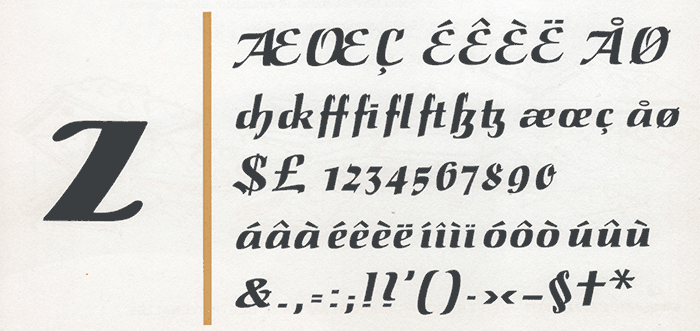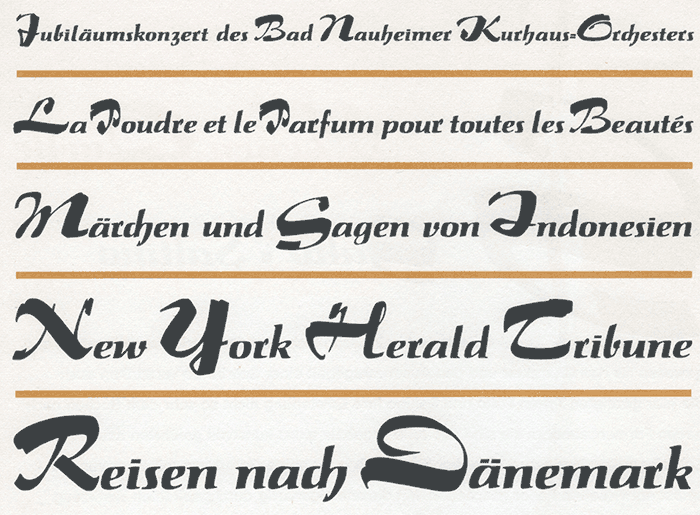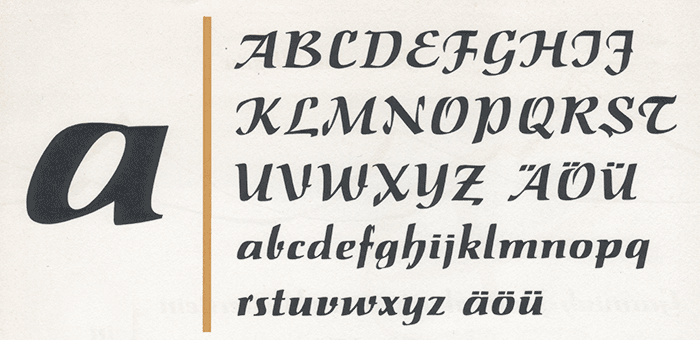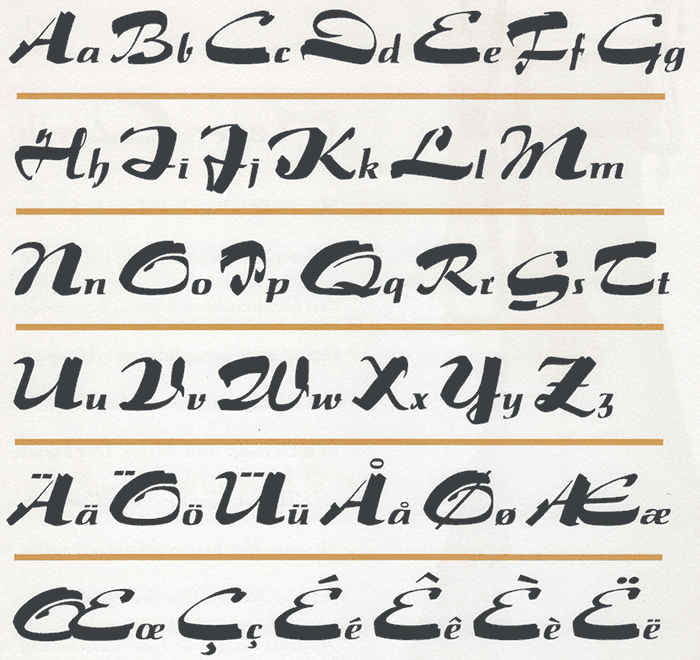
- 1952
- Antiqua Schreibschrift
Die zusammengehörigen Schriften Salto und Saltino erschienen ab 1952 bei der Schriftgießerei Gebr. Klingspor. Die Kleinbuchstaben wurden mit einer von Hoefer eigens entwickelten Breitfeder entwickelt. Je nachdem, welche Großbuchstaben man dazu kombinierte, wurde die Schrift dann Salto oder Saltino genannt. Während die Saltino-Versalien im Stile der Minuskeln geschrieben sind, wurden die charakterstarken Salto-Versalien mit einem Pinsel geschrieben. »Dabei bringt sie eine Frische und Keckheit in die Typographie, die vor allem von Werbeschaffenden besonders geschätzt wird« hieß es in einer Broschur von Stempel.
Saltino, Bleisatzschriftmuster
Salto, Bleisatzschriftmuster